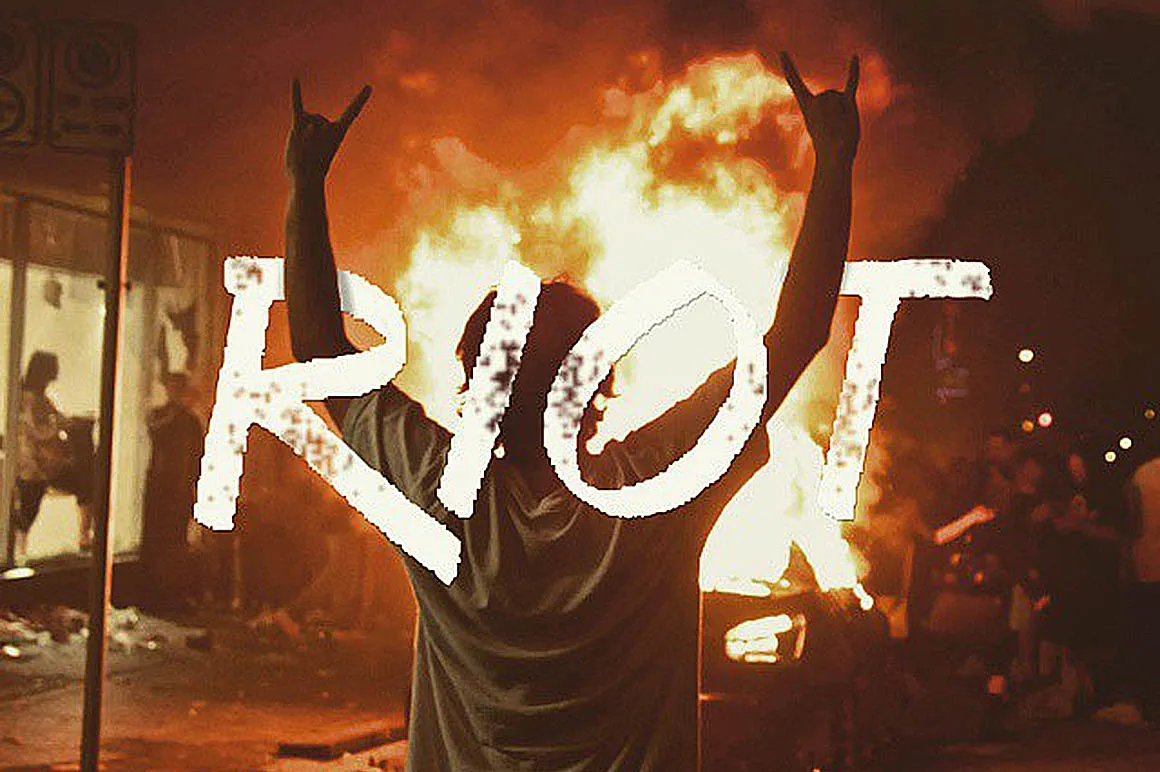
A Bruss Typeface é uma elegante seleção de linhas curvilíneas e expressivas que se inspiram na arte das ferramentas de traçado, criada pelo designer Hamilton. Suas formas fluidas e vibrantes permitem um design atraente para diversos projetos visuais, especialmente nas áreas de identidade visual e criação digital. Esta fonte é perfeita para quem deseja dar um toque único aos seus trabalhos com texto, seja em postagens no Instagram ou para o projeto do site da sua empresa. A Bruss oferece uma mistura única de elegância e espírito criativo que combina bem com muitos estilos design modernos. Descarregue-a agora e experimente a brilhante diferença dela em seus projetos!